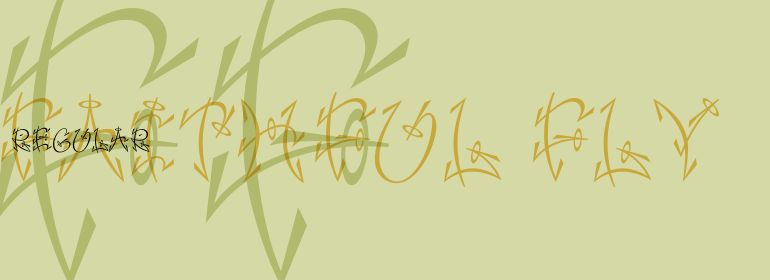
Faithful Fly™
Faithful Fly™,这款字体结构工整、笔画清晰,兼顾美观与易读性,适用于标题、正文、海报、包装、LOGO 等多种场景。字形优雅稳定,风格百搭耐看,适配日常排版与创意设计,让文字呈现更舒适、更具质感。Faithful Fly™一笔一画,皆是细节,以均衡的比例、流畅的线条打造舒适视觉体验,字形端正大气,风格简约现代。无论是商业设计、品牌宣传还是日常排版,都能轻松驾驭,让文字更有格调与力量。Faithful Fly™字体下载。
字体品牌: ITC(Monotype) 设计师:Sagorski,David 字体分类:衬线体 字体属性:外文 字符集:Unicode 发布时间: 2018